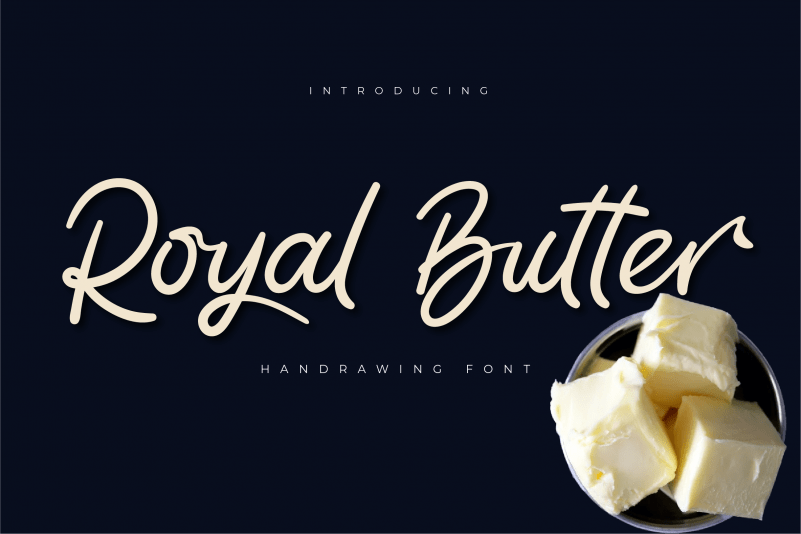
Royal Butter Script Font – Download Grátis
A Royal Butter Script Font é uma delícia para os amantes da escrita à mão que procura algo sofisticado e encantador. Essa fonte criativa não só adicionará um toque de elegância ao seu design, mas também tornará qualquer trabalho em papel mais especial e memorável. Que tal usar essa fonte para criar uma assinatura única para seus cartões de visita? Ou até mesmo personalizar suas próximas invitations de casamento ou cards de agradecimento com um toque autêntico de escrita à mão? Esta fonte, que tem seu próprio conjunto de recursos PUA (Personal Use Association), significa que você terá acesso a todos os símbolos e frases alternativas, garantindo que suas criações continuem sendo surpreendentes. A Royal Butter Script Font é perfeita para aqueles desejosos de dar um toque único às mais variadas aplicações gráficas. Seja ela uma lembrança de casamento personalizada ou apenas um cartão de agradecimento, sua elegância irá impressionar seu público-alvo. E você sempre terá alternativas estilosas para escolher.